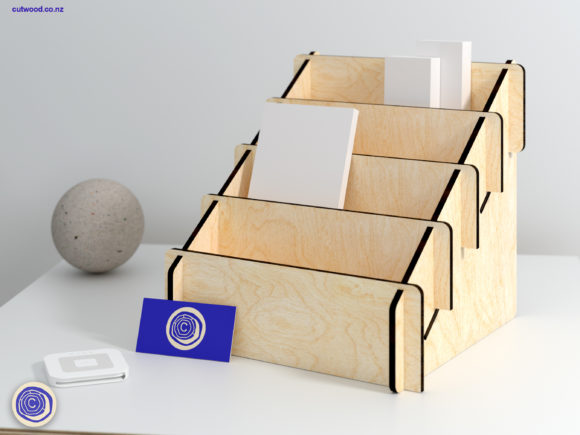
Retail Counter Display
قد يكون العثور على عناصر التصميم المناسبة أمرًا صعبًا، ولكن Retail Counter Display يقدم مجموعة استثنائية ترتقي بعملك على الفور.
سواء كنت تقوم بإنشاء منتجات الطباعة عند الطلب أو دعوات الزفاف أو رسومات وسائل التواصل الاجتماعي، فإن Retail Counter Display هو الخيار المثالي.